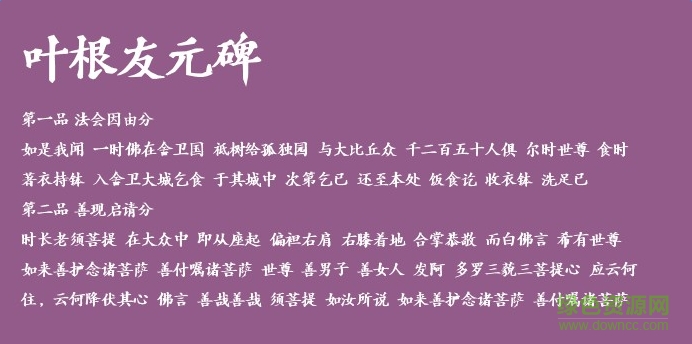
葉根友元碑字體是一款古典文雅風(fēng)格字體軟件,元碑體筆畫工整整齊配上粗粗的字體,非常的醒目,一般用于商業(yè)機(jī)構(gòu)標(biāo)題文章的書寫,比較正式,還有更多好看字體歡迎來(lái)綠色資源網(wǎng)下載體驗(yàn)!
葉根友元碑字體端正大方得體,整體效果出眾,字庫(kù)完整,全部數(shù)字、大小寫字母及通用標(biāo)點(diǎn)符號(hào),符合國(guó)家標(biāo)準(zhǔn)GB2312編碼,能夠適用于產(chǎn)品包裝、廣告宣傳、出版印刷、商標(biāo)用字、商業(yè)網(wǎng)站、影視影像視頻、書籍出版印刷等,有需要的朋友可以免費(fèi)下載收藏。
該字體非常正規(guī),繼承傳統(tǒng)楷書的優(yōu)美特點(diǎn),筆畫粗壯有力,非常好看!